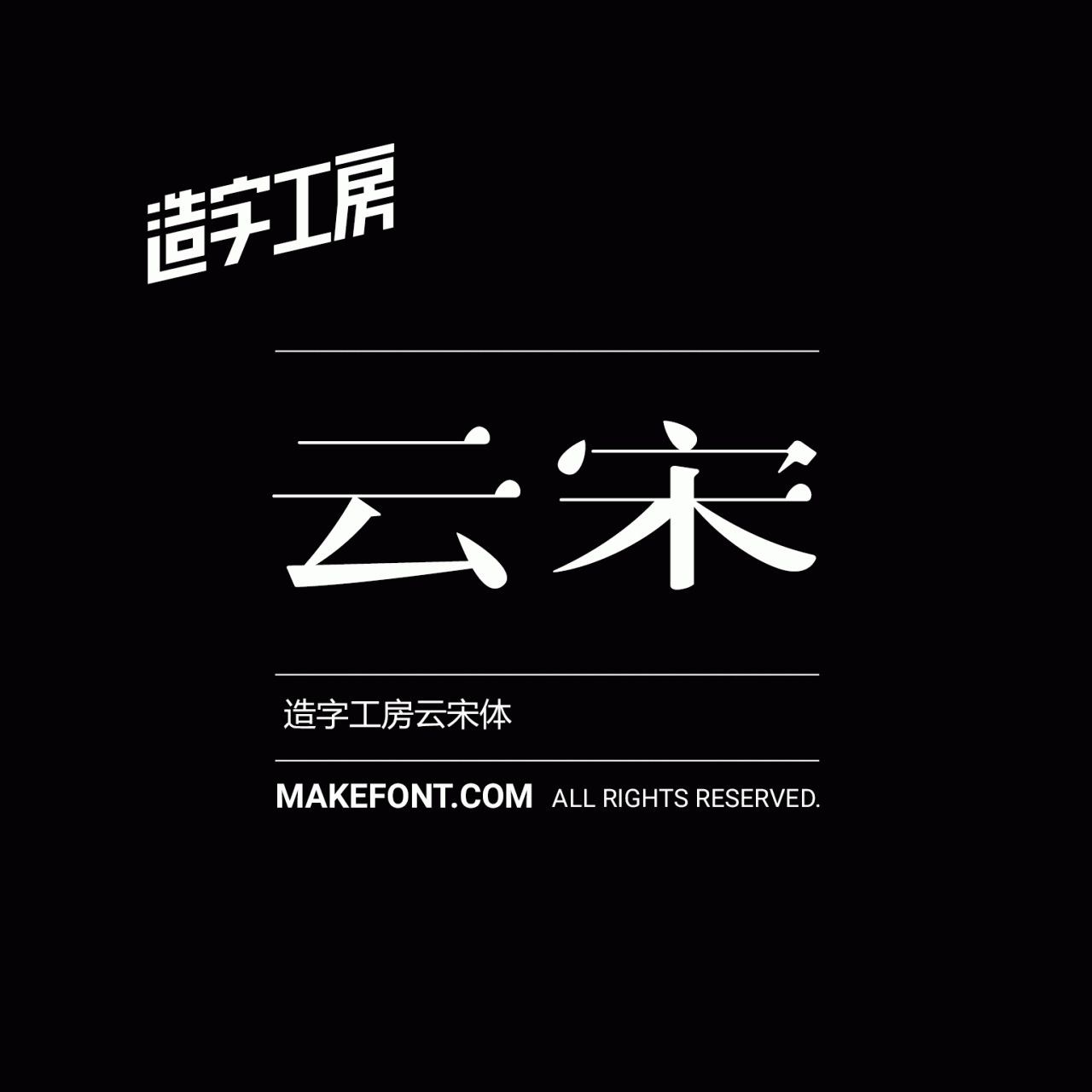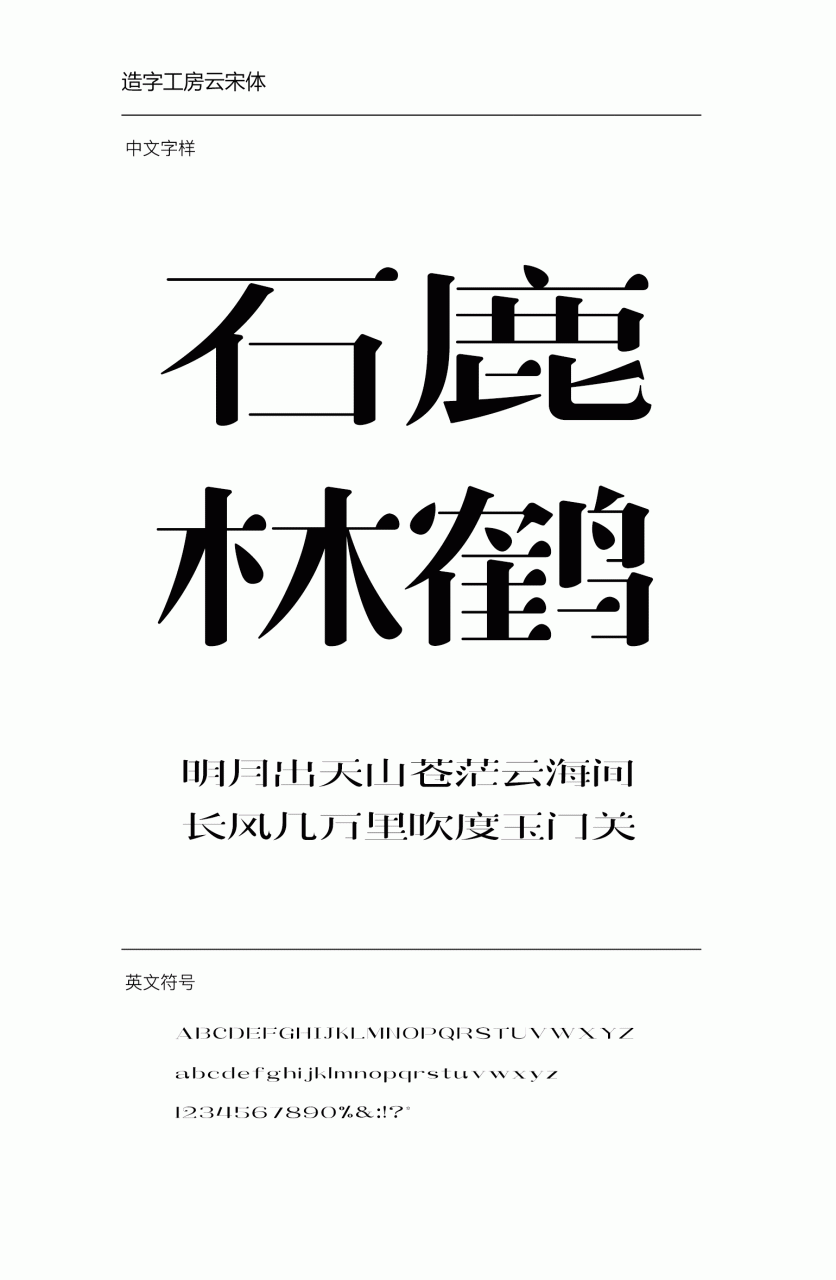
造字工房云宋常规体设计说明
造字工房云宋体横细竖粗,笔画新颖独特,恰如待放荷苞的点与横右端的“露滴”相得益彰,互相呼应,增强一份意境。结构上采用扁体,笔画之间分离,但不影响字形的识别性。整套字体清新雅淡,情趣盎然。此款字体适用于标题、广告或正文用字。有着极强的应用空间。本字体为简体字库,采用OpenType/CID格式,Adobe-GB1-5编码。基于中华人民共和国GB2312-80字符集标准,另按需添加101个汉字。共收容字数6864CJK汉字,ASCII常用字符100个。